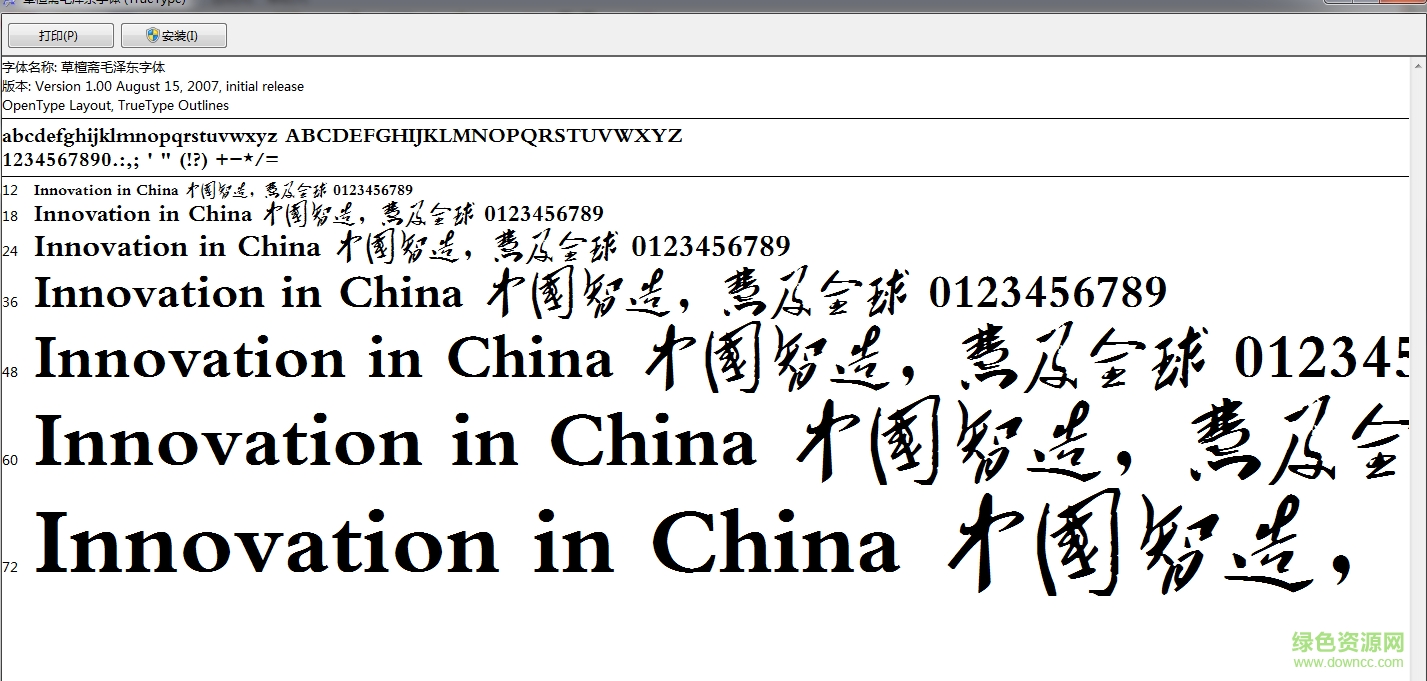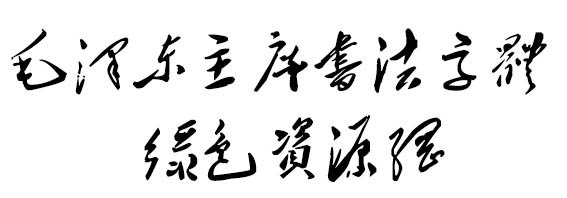
毛澤東主席書(shū)法字體是許多朋友都在尋找的優(yōu)秀字體文件,毛澤東二十世紀(jì)杰出書(shū)法家,他的書(shū)法在中國(guó)書(shū)法史上占據(jù)著重要地位,以其大氣磅礴,氣貫長(zhǎng)虹的風(fēng)格,深受廣大書(shū)法愛(ài)好者的喜愛(ài),需要的用戶快到綠色資源網(wǎng)下載體驗(yàn)吧
江蘇徐州禚效鋒先生用了四個(gè)月的時(shí)間,成功開(kāi)發(fā)了毛澤東電腦字,填補(bǔ)了字體開(kāi)發(fā)的空白,為字體開(kāi)發(fā)作出了貢獻(xiàn)。據(jù)悉,毛澤東電腦字體將于8月15日在書(shū)法熱線、書(shū)法縱橫、中國(guó)書(shū)法論壇、中國(guó)書(shū)法家論壇、中國(guó)書(shū)法網(wǎng)等網(wǎng)站發(fā)布發(fā)布測(cè)試版。10月1日發(fā)布《毛澤東字體正式版》,可供廣大喜愛(ài)毛澤東字體的書(shū)法愛(ài)好者免費(fèi)下載。